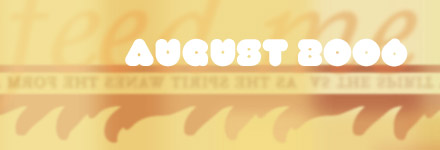
Erkenntnisse zum Registrierungszeichen ®
Gestern schrieb mir Jan Dambach folgende E-Mail: »Ich arbeite gerade als Ferienjobber in einer Druckerei... Dort muss ich Produktmappen für die Heidelberger Druckmaschinen AG kleben. Die schreiben dort ›Speedmaster®‹. Allerdings das ® hochgestellt. Der Chef dort meinte, das wäre immer hochgestellt. Was sagt der Typograph?«
Heute morgen dachte ich ›Eine einfache Frage‹, greife zu verschiedenen Fachbüchern, unter anderem zu Detailtypografie von Forssmann/de Jong. Ich erfuhr jede Menge über die Bedeutung des ®-Zeichens und dass es »kompress oder leicht gesperrt am geschützten Namen« steht. Über die Form bzw. seine Grundlinie finde ich allerdings keinerlei Hinweise.
Also nähere ich mich der Antwort auf andere Weise: Die geladenen Lieblingsschriften schreiben und deren ® unter die Lupe nehmen. Ich bin überrascht. Noch vielfältiger als die Stile der Schriften ist die Interpretation des ®-Zeichens. Mal klein und hoch (FF Acanthus, Rotis, Bello), mal groß und kaum hoch gestellt (FF Din, Frutiger Next, FF Meta), im Falle der FF Scala sogar (optisch) tief gestellt und bei der Parable ist das ® größer als die Versalien. Na prima. Keine Regeln? Alles beliebig? Nein!
Zunächst einmal: Über Aussehen und Position des Zeichens entscheiden alleine die Schriftentwerfer. Wenn irgendwelche »klugen« Office-Programme (oder -User) meinen, sie müssten das Symbol wie eine hochgestellte Ziffer behandeln, mit den entsprechenden Kaputtmach-Mechanismen (z. B. Verkleinerung), gehört denen auf die Finger geklopft.
Da es sich bei dem ® nicht um einen Buchstaben sondern um ein Sonderzeichen handelt, genießt es beim Entwurf mehr Freiheitsgrade ... daher die Vielfalt der Interpretationen. Mein kleiner, absolut nicht repräsentativer Text lässt darauf schließen, dass das ® bei Antiqua-Schriften kleiner und »hochgestellter« interpretiert wird als bei Sans-Serifs. Ausnahmen bestätigen die Regel (FF Scala). Die Schrift FF Parable, ein Lesbarkeitswunder, wurde für das Setzen von Texten unter 8 Punkt optimiert, und tatsächlich sieht eine 7 pt Parable-Text wie eine 10 pt Times aus (siehe Abbildung).
Ich habe auch gelernt, dass ein und derselbe Schriftentwerfer sein ® unterschiedlich interpretiert. Erik Spiekermann bezeichnete seine junge FF Unit stets als die Schwester der über 20 Jahre alten FF Meta. Gleichwohl legte er das ® in beiden Schriften völlig unterschiedlich an. Auch hier liegt die Begründung im Anwendungszweck und in der Drucktechnik begründet. Meta entwarf Spiekermann ursprünglich für das Setzen von Telefonbüchern, die auf schlechtem Papier mit High-Speed-Druckern produziert wurden: großes ®-Zeichen. Unit erblickte das Licht der Welt im Digitalzeitalter, wo Offset-Druck-Maschinen messerscharfe Schriftbilder liefern, PDFs brillant auf Bildschirmen erstrahlen und Tintenstrahldrucker mit 1200 dpi und mehr ausgeben: kleineres ®-Zeichen. Warum sein Unit-® allerdings oval statt rund ist, diese Frage muss er uns selbst beantworten.
Trotzdem plakatiert die SPD wie immer und wie alle
anderen Parteien auch, nämlich nervig, unausweichlich
und die Wähler für dumm verkaufend. Das zurückgelegte
Geld muss ja schließlich ausgegeben werden.
Die Großplakate der SPD entwickeln sich in der Hauptstadt zur Lachnummer. Auch mich regen sie zum Fantasieren an, wenn ich an ihnen vorbei rausche.
»Wenn ick meine BZ lese, will ick nüch jestört werdn, klar?«
»Dit is jenau mein Humor: Zeitung lesen und den Augenkontakt zur Kundschaft konsequent vermeiden.«
»Hätt’ ich nie gedacht, dass sich die Experimente für die Airbus-Statik zu ein Bruchteil der Kosten mit Fischer-Technik durchführen lassen. Das müssen wir dem Senator für Forschung natürlich nicht auf die Nase binden.«
»Weil mir der Baukasten gestern um die Ohren geflogen ist, muss ich jetzt diese dämliche Schutzbrille tragen.«
Dazu: Die Glosse Wahrheit und Wahlplakate in der Berliner Zeitung und eine Frage im Spreeblick.
»Da, ihr Lieben, liegt Rumänien ... und dort geht es den Kindern viel schlechter als bei und in Berlin.«
»Du, Tante Renate: Wie lange müssen wir in diesem Plattenbau mit den bunten Jalousien noch eingesperrt bleiben?«
»Ich hab’ mich auf der Fanmeile in Klinsi verliebt. Seitdem besucht er mich alle 14 Tage in meiner Dachgeschoss-Wohnung am Kollwitzplatz.«
»Als die Berliner Bank die Finanzierung unserer Eigentumswohnung übernahm, haben wir sofort unser Studium abgebrochen. Inzwischen leben wir ganz gut von den Mieteinnahmen unserer 7 Objekte.«